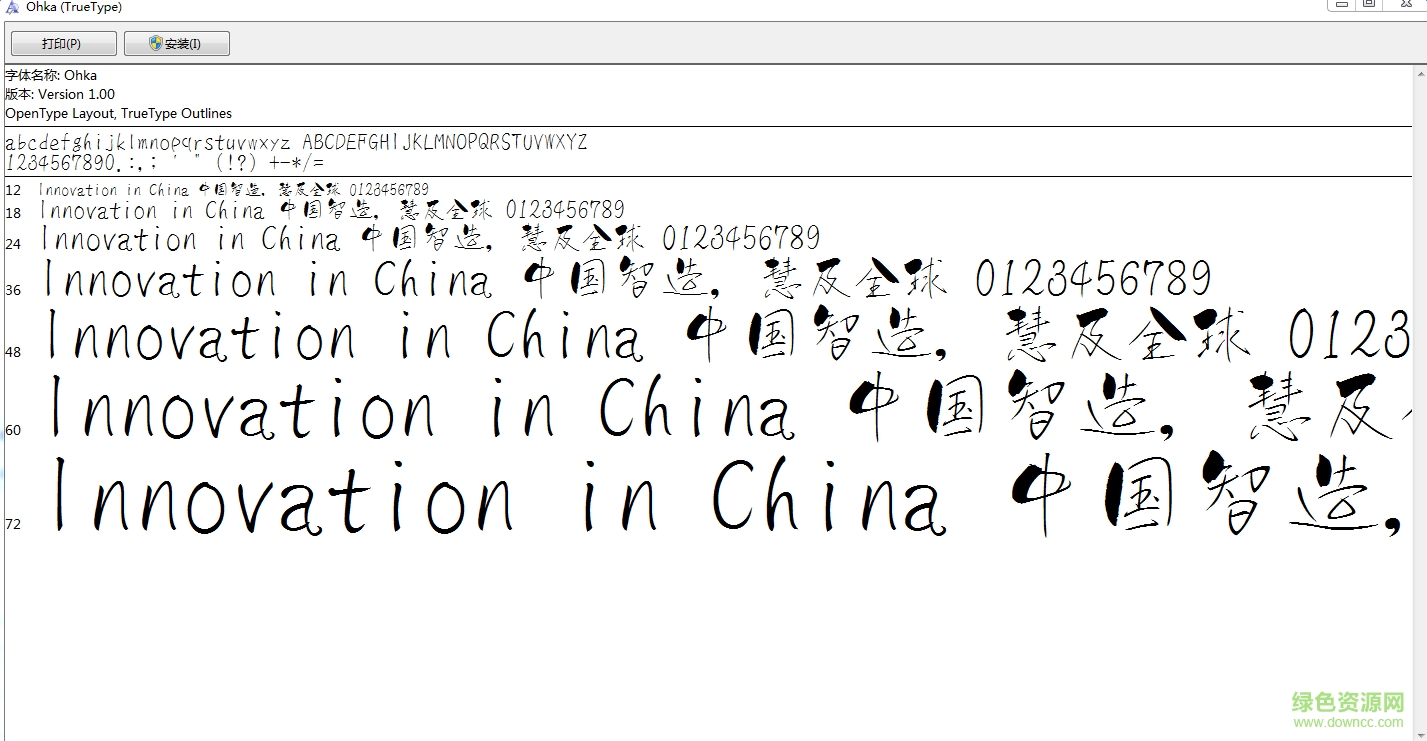
軟件介紹 軟件標簽: 白舟櫻花字體 白舟字體 白舟櫻花書體字體是一款非常漂亮的字體,筆畫粗細相稱,線條流暢優(yōu)美,字形清秀大方,適用于廣告、海報、包裝等設計領域,需要該字體的朋友快來綠色資源網(wǎng)下載吧!字體安裝方法方法一:控制面板/字體/文件/安裝新字體;方法二:直接將字體復制到C:\WINDOWS\Fonts。方法三:針對win7系統(tǒng),用戶只需選中字體右鍵安裝即可。注意事項本站所有字體資源僅供個人學習與參考,如需商業(yè)使用請到相關官網(wǎng)授權。 軟件截圖 上一張下一張(1 / 1) 安裝詳細截圖 猜你喜歡 非主流字體 花字體 非主流字體 非主流字體大全收錄了國際音標字體ipapanadd、五線譜字體akvo.ttf、等寬編碼字體、立體英文字體、eva明朝體、特殊黑體字體、英文花體字體等各式好看的非主流字體,中英文都有! 查看更多>> code free font 2.44M/中文/5.0/下載 ipapanadd.ttf 250KB/中文/1.0/下載 akvo.ttf字體 120KB/中文/2.2/下載 englishling字體 2.44M/中文/1.9/下載 vineta bt普通(西方) 95KB/中文/5.0/下載 eva明朝體 23.43M/中文/1.0/下載 花字體 花朵字體形狀特殊,整體給人非常喜慶的感覺,但好多用戶抱怨找不到合適的花朵字體,特此小編整理了庫里面比較熱門的花字體,提供給廣大網(wǎng)友,希望能滿足大家的藝術范! 查看更多>> 盛世花開體 6.94M/中文/10.0/下載 移花別戀體 7.61M/中文/10.0/下載 三生三世十里桃花字體 6.27M/中文/4.0/ttf版下載 伯樂花香體 2.06M/中文/10.0/下載 花漾字體ttf 5.42M/中文/10.0/下載 墨染蓮花碎字體 5.85M/中文/10.0/下載 其他版本下載 標題 大小 更新日期 下載 下載地址 電腦版 白舟櫻花書體 點擊報錯 軟件無法下載或下載后無法使用,請點擊報錯,謝謝! 關閉報錯反饋 請描述您所遇到的錯誤,我們將盡快予以修正,謝謝! *必填項,請輸入內(nèi)容 本類最新 dreamweaver字體庫 首爾南山體字體 v1.06 官方版 潮字社風云簡ttf 潮字社凌渡鯤鵬簡體字體 潮字社曾玉波手書簡字體 微博慧心字體 相關文章 300英雄櫻花地圖補丁怎么用,附圖文教程 用戶評論 熱門評論 最新評論 發(fā)表評論 查看所有評論(0) 昵稱: 請不要評論無意義或臟話,我們所有評論會有人工審核. 字數(shù): 0/500 (您的評論需要經(jīng)過審核才能顯示)